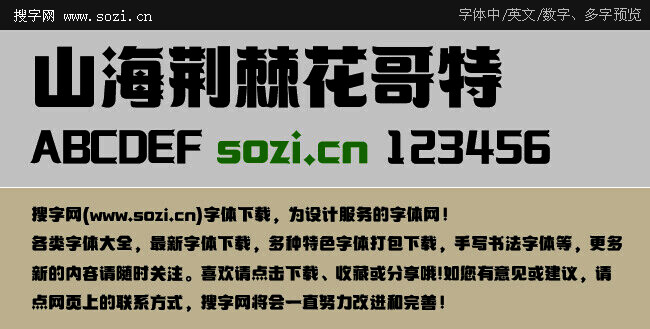
山海荊棘花哥特
搜字網(wǎng)提供一款山海荊棘花哥特中文藝術(shù)字體下載,山海荊棘花哥特是一款哥特風(fēng)字體,包含簡(jiǎn)體漢字6763個(gè)。該字體融合了西方哥特元素,字體獨(dú)特,新穎華麗。漢字藝術(shù)與西方文字的融合,如夜空中閃爍著暗黑光芒;個(gè)性鮮明的字體特征,散發(fā)著神秘而高冷的氣息。在華麗而不失婉約中,感受哥特風(fēng)的魅力。適合包裝設(shè)計(jì)、海報(bào)設(shè)計(jì)、廣告設(shè)計(jì)等應(yīng)用。